随着马赛足球俱乐部发布全新2020/21赛季主客场球衣并将其摆上俱乐部商店的货架,我们发现新赛季法甲联赛将启用全新的字体球衣号码,同时还将启用全新的联赛赛事标识。
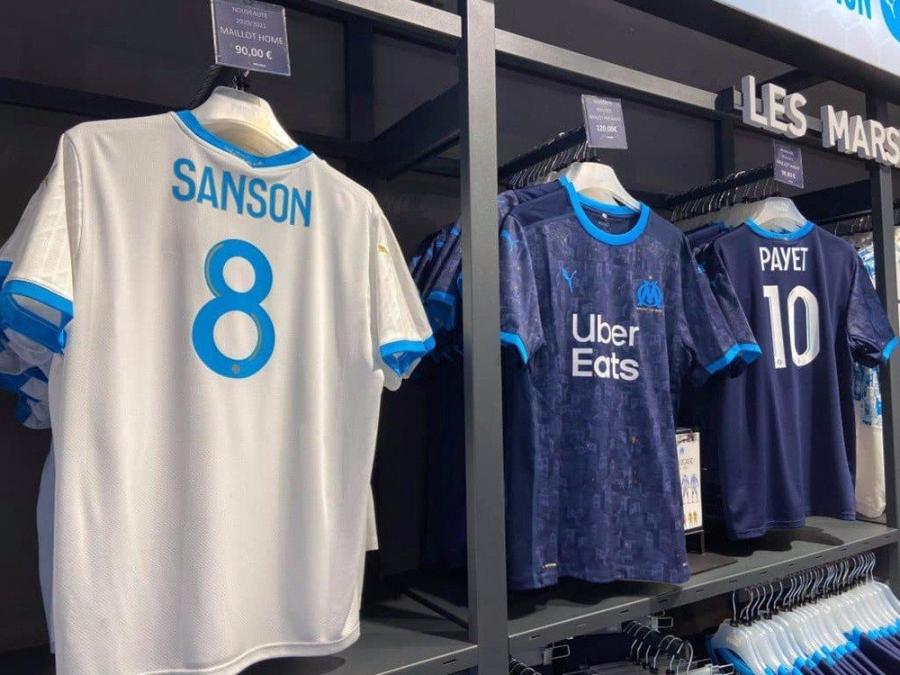
已经摆上俱乐部商店货架的马赛2020/21赛季主客场球衣上已经印制了新赛季联赛球衣号码与球员姓名,与上赛季的球衣号码和球员姓名相比,新赛季球衣印字的字体看起来更具现代感,并且号码与字母中还加入使其更具立体感的条纹。并且号码底部还加入了一个全新标识,按照上赛季球衣号码推断的话,这个以六边形呈现在人们面前的标识应当是全新法甲联赛的赛事标识。
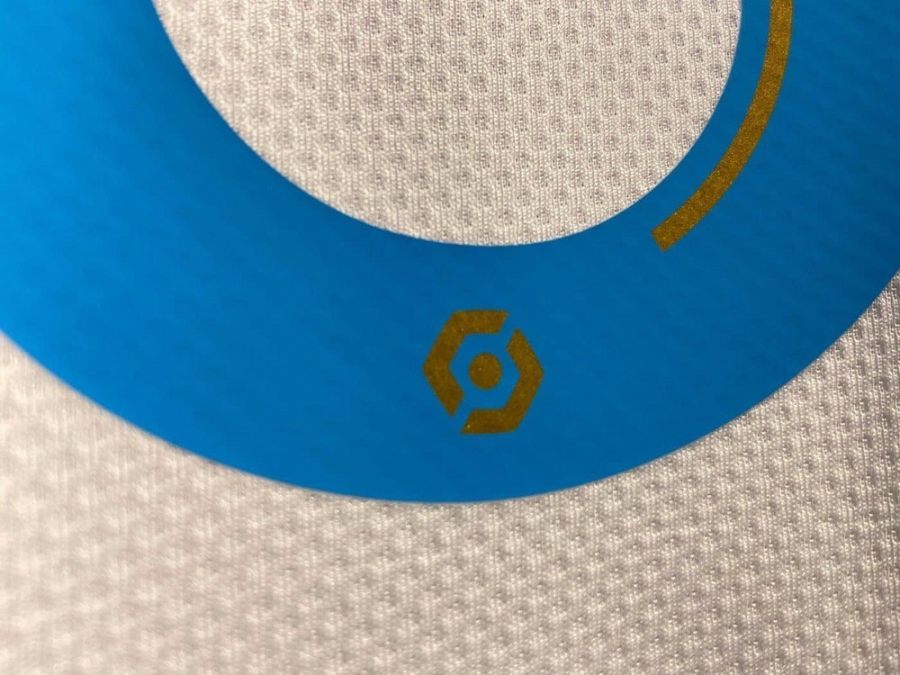
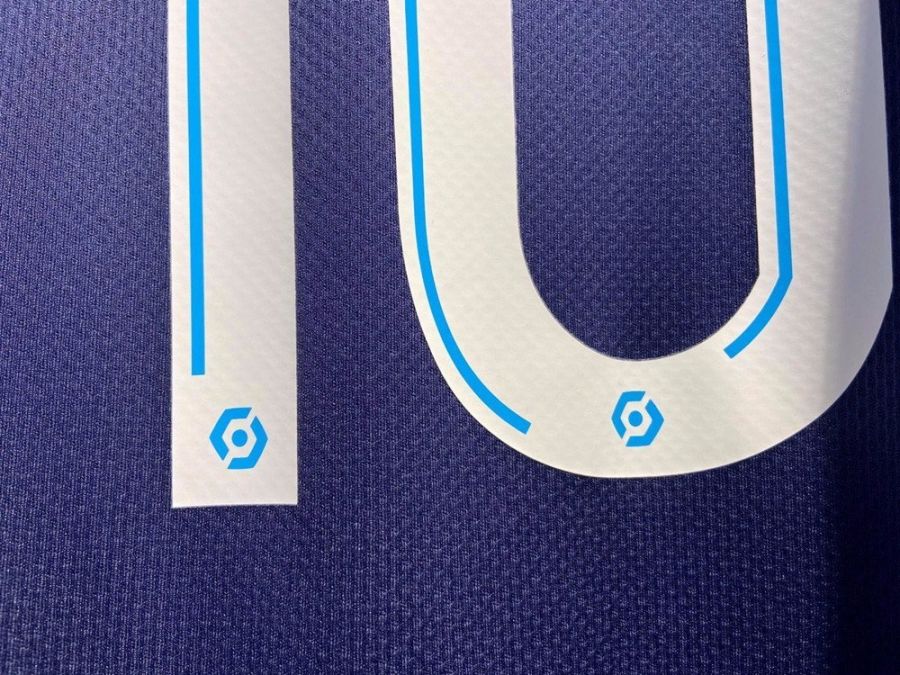
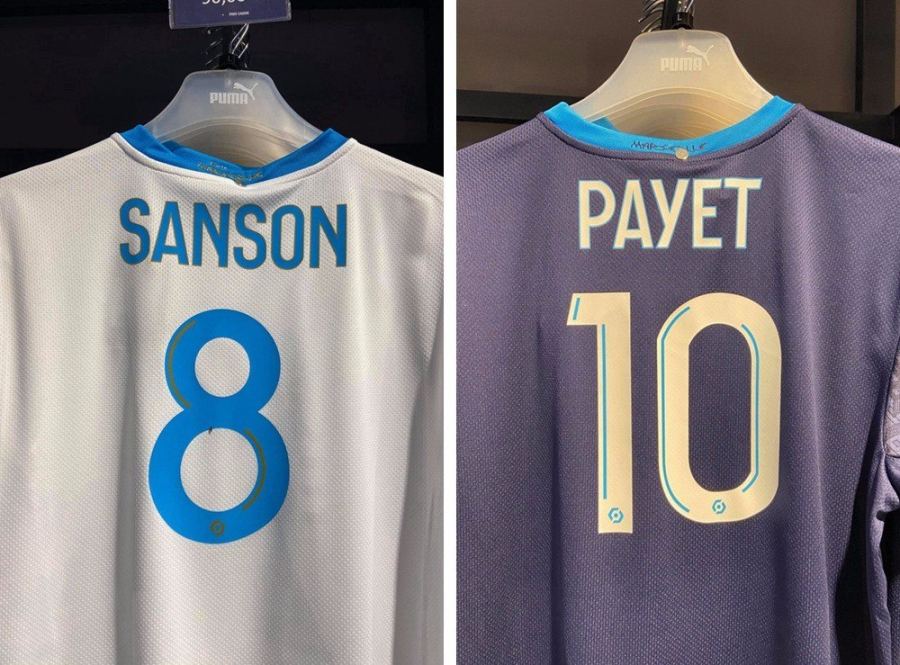
球衣上的数字印刷字体是不是很好看,新赛季球衣印字的字体看起来更具现代感,并且号码与字母中还加入使其更具立体感的条纹。并且号码底部还加入了一个全新标识,按照上赛季球衣号码推断的话,这个以六边形呈现在人们面前的标识应当是全新法甲联赛的赛事标识。
随着马赛足球俱乐部发布全新2020/21赛季主客场球衣并将其摆上俱乐部商店的货架,我们发现新赛季法甲联赛将启用全新的字体球衣号码,同时还将启用全新的联赛赛事标识。哪里可以下载字体字库呢?大家是不是跟我一样想文呢?